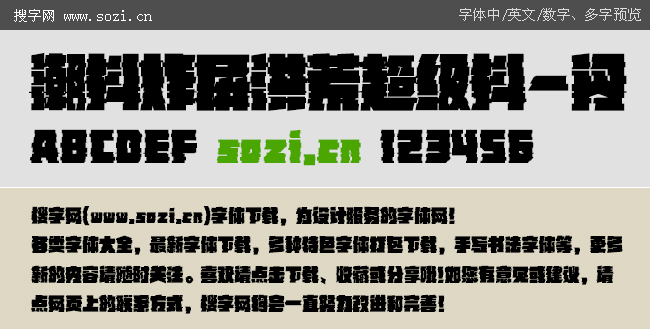
潮抖炸屏洪荒超級抖-閃
搜字網(wǎng)提供一款潮抖炸屏洪荒超級抖-閃中文字體下載,潮抖炸屏洪荒超級抖-閃是一款中文藝術(shù)字體,潮抖炸屏洪荒超級抖以藝術(shù)字體為基準(zhǔn),加入抖動筆畫與切割錯位效果,潮流動感,重新定義時尚字體。適合用于標(biāo)題設(shè)計(jì)、海報設(shè)計(jì)、包裝設(shè)計(jì)等場景廣泛應(yīng)用。(本字體為個人非商用版,商用請聯(lián)系作者購買授權(quán)。官方網(wǎng)址:http://www.reeji.com 聯(lián)系方式:021-58597892)